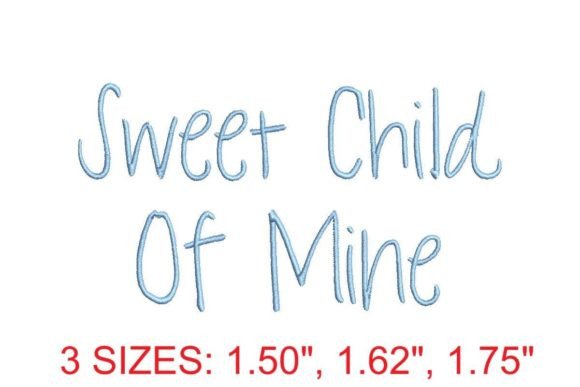
Sweet Child of Mine Font
Het vinden van de juiste ontwerpelementen kan lastig zijn, maar Sweet Child of Mine Font biedt een uitzonderlijke collectie die uw werk direct naar een hoger niveau tilt.